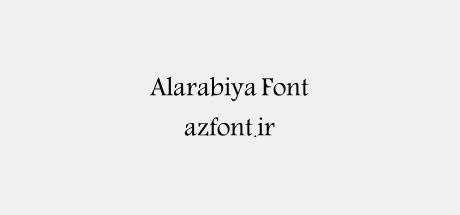
Alarabiya Font
فونت زیبای رایگان Alarabiya Font
قلم زیبای Alarabiya Normal Font از سری قلم های بسیار زیبا برای تایپوگرافی و لوگو تایپ می باشد.این قلم در وزن Normal و توسط طراحی و منتشر شده است.